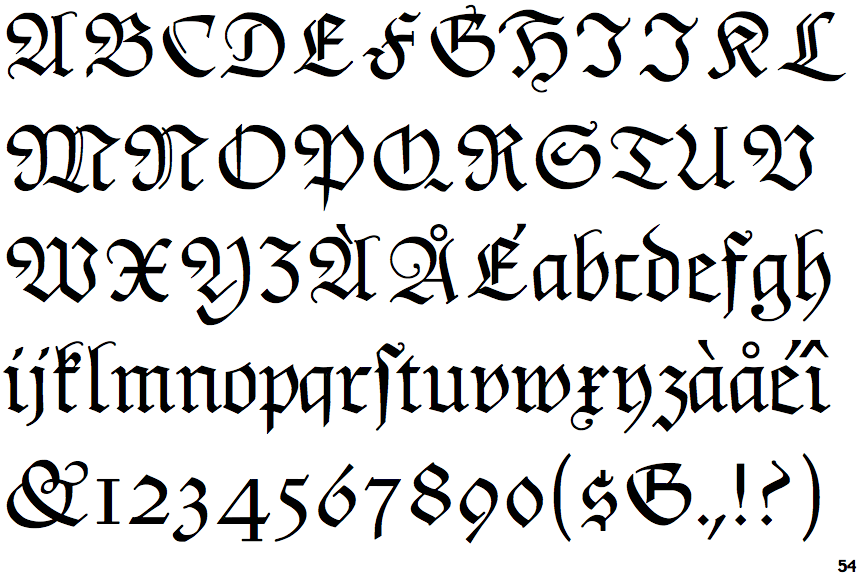
Foundry: Monotype
Designer: Yeend, Richard
Laut Linotype hat er die nicht designt. Auch Fonts.com kennt die Schrift nicht von ihm. Laut Luc Devroye (bei ihm heisst die Schrift Honerswerda) könnte er die auch für Agfa designt haben.
Das Klingspor-Museum kennt die Schrift von ihm und ordnet sie den Publishern Monotye und Linotype zu. Vielleicht sind die Rechte bei all den Akquisitionen verloren gegangen und deswegen ist die Schrift nicht mehr auffindbar?